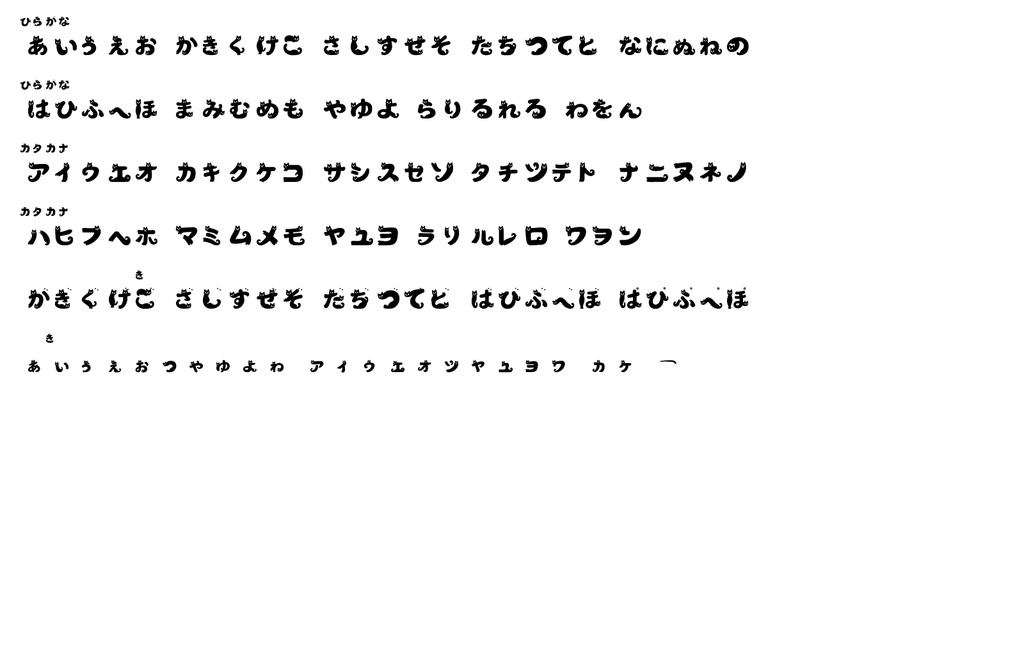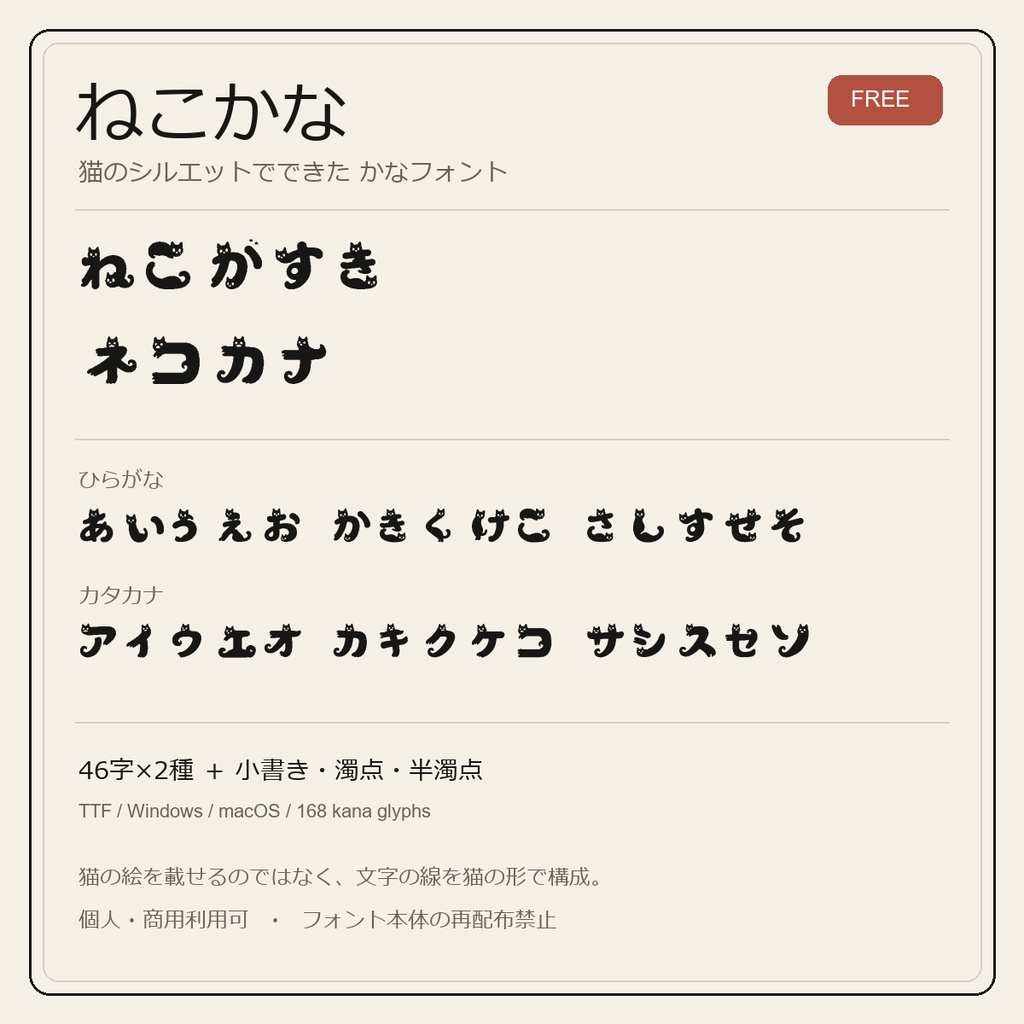
ねこかな|猫のシルエットでできたかなフォント【無料】
猫のシルエットが文字の画そのものになる、白黒のかなフォントです。猫の絵を背景に置いて文字を重ねるのではなく、黒い文字輪郭を猫の頭・背・胴・尾・肉球で構成し、白い部分を目や口元、腹の抜きとして使っています。 ■ 収録内容 ・ひらがな46字、カタカナ46字 ・小書きかな、濁点・半濁点付きかな、長音符「ー」 ・合計168文字。詳しい対応文字は同梱READMEをご確認ください。 ■ 収録外 漢字、英数字、句読点、一般記号は収録していません。かな見出し、ロゴ、短いタイトル向けの装飾フォントです。 ■ ファイル形式 TrueType(TTF)、フォント見本、92基本かなそれぞれの猫パーツ設計指示、README・利用条件をZIPに収録。 ■ 利用条件 個人・商用利用可。ロゴ、動画、ゲーム、印刷、配信、同人・商業作品に使用できます。クレジット不要です。フォントファイル自体の再配布・共有・転売は禁止です。詳細はZIP内のLICENSE.txtをご確認ください。